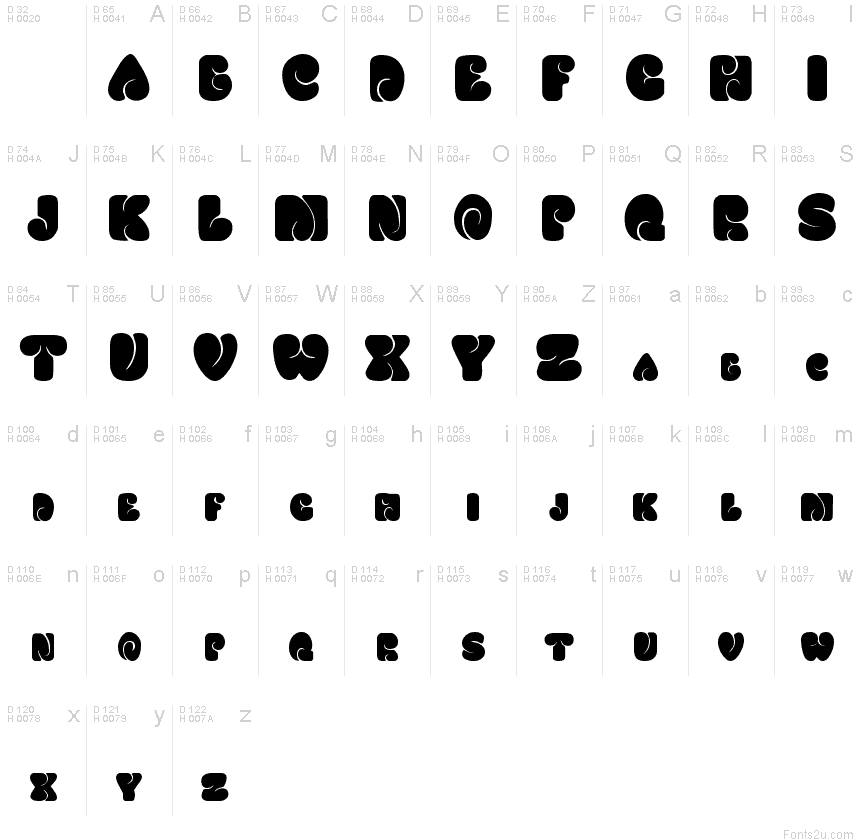
FATSOcaps è un font display gratuito in stile groovy, con lettere che ricordano gocce di vernice densa, congelate un istante prima di colare. Ogni carattere si gonfia in macchie corpose e cariche d'inchiostro, con curve fluide e piccoli tagli interni netti che impediscono un aspetto goffo. Il ritmo delle maiuscole è audace e vivace: anche una sola parola colpisce come un logo.
Questo font gratuito risplende su poster ispirati agli anni '70, flyer, copertine di album, branding retrò, packaging alimentare e grafiche social che richiedono una voce forte e giocosa. Usa FATSOcaps in grandi dimensioni per lasciare che quelle forme bulbose respirino; abbinalo a un carattere sans serif geometrico pulito per i testi più piccoli, garantendo così la leggibilità. FATSOcaps trasforma qualsiasi frase breve in un segno grafico memorabile, vischioso e d'impatto.